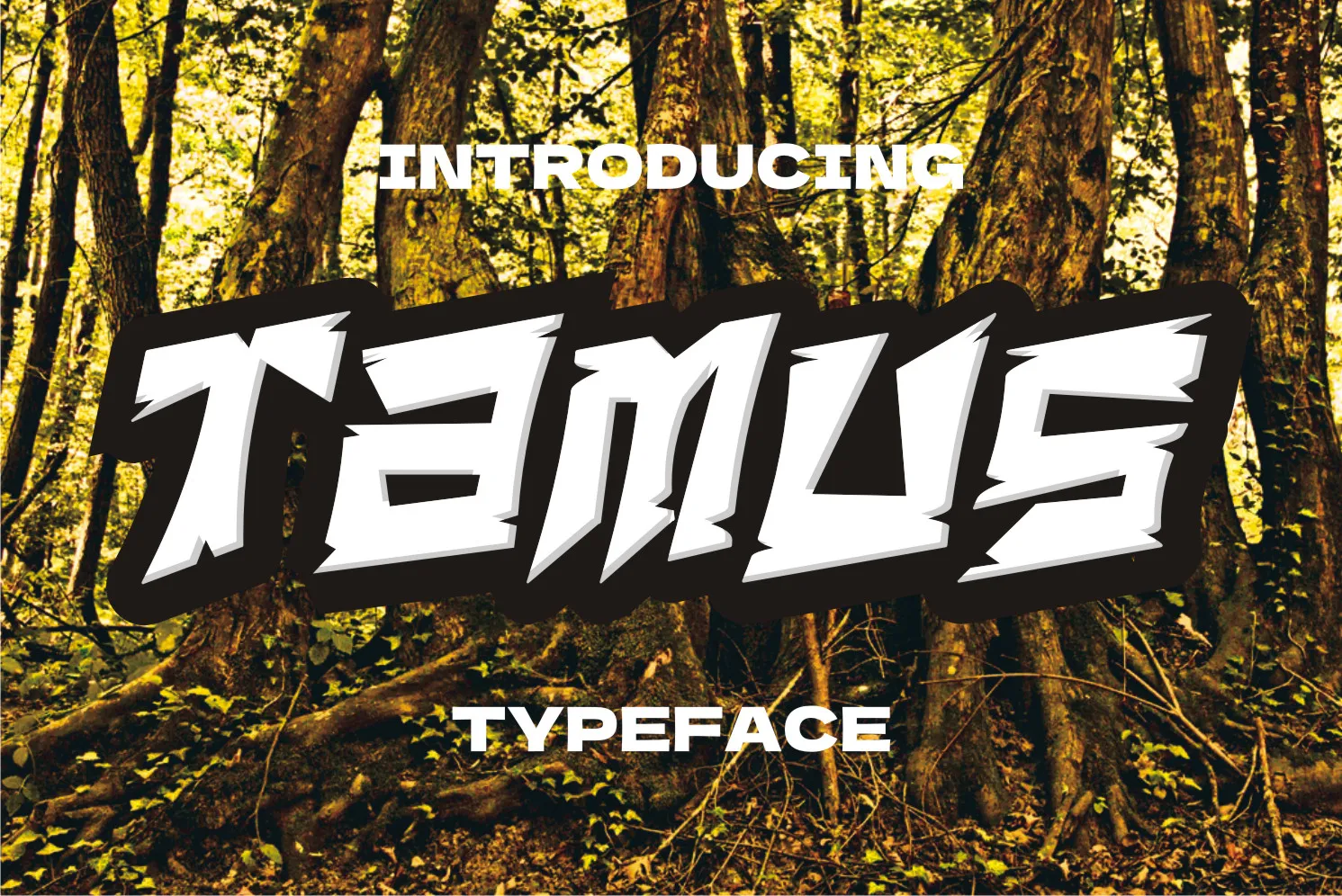
Tamus Font – Download Grátis
Aqui está uma descrição natural e envolvente para a página de download da font ‘Tamus Font’, focando na categoria de fontes decorativas: A Tamus é uma fonte elegante que se destaca pela sua simplicidade e sofisticação. Ela se encaixa perfeitamente em projetos decorativos, especialmente quando usada em t-shirts descoladas, roupas esportivas modernas ou até mesmo no desenvolvimento de logomarcas para marcas queridinhas da moda. Seja você um designer criando uma camiseta chamativa e estilosa para seu site de roupa casual, ou alguém buscando uma fonte atraente para criar uma identidade visual para sua marca, Tamus certamente pode atender às suas necessidades. Seja em um poster de propaganda, um banner em uma loja de moda da moda, ou até mesmo na etiqueta de seu próximo par de tênis preferido – a Tamus será o alvo perfeito para expressar sua personalidade e estilo. Ela é ideal tanto para os fãs de streetwear quanto aqueles que buscam um toque sofisticado em suas criações, garantindo uma combinação única entre destaque e elegância.
Designer: letterfiastudio